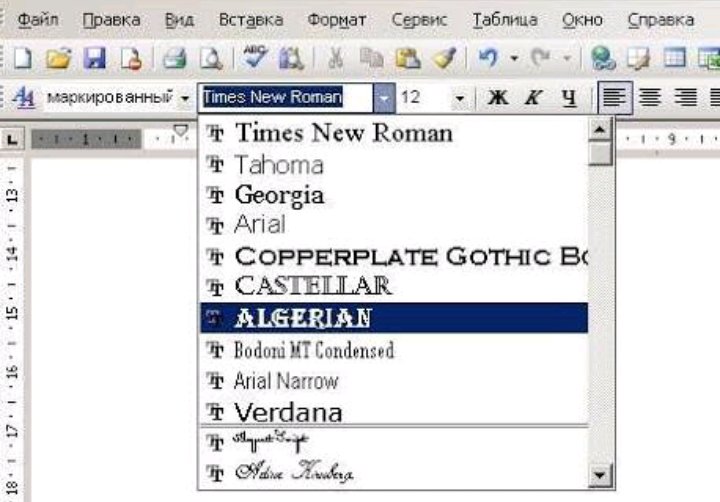
Браузер посетителя может отобразить только те шрифты, которые установлены в его операционной системе.
На этой странице приведен список русифицированных шрифтов, включённых в каждую версию Windows. Такие шрифты называют безопасными шрифтами для браузеров.
| Шрифт | — Arial |
| Шрифт | — Arial Cyr |
| Шрифт | — Arial Black |
| Шрифт | — Book antiqua |
| Шрифт | — Bookman old style |
| Шрифт | — Calibri |
| Шрифт | — Cambria |
| Шрифт | — Candara |
| Шрифт | — Century |
| Шрифт | — Century gothic |
| Шрифт | — Comic Sans Ms |
| Шрифт | — Consolas |
| Шрифт | — Constantia |
| Шрифт | — Corbel |
| Шрифт | — Courier |
| Шрифт | — Courier New |
| Шрифт | — Courier, monospace |
| Шрифт | — Cursive |
| Шрифт | — Franklin Gothic |
| Шрифт | — Gabriola |
| Шрифт | — Garamond |
| Шрифт | — Georgia |
| Шрифт | — Helvetica |
| Шрифт | — Impact |
| Шрифт | — Lucida console |
| Шрифт | — Lucida Sans Unicode |
| Шрифт | — Mistral (Mistral) |
| Шрифт | — monospace |
| Шрифт | — Monotype Corsiva |
| Шрифт | — MS Sans Serif |
| Шрифт | — MS Serif |
| Шрифт | — Palatino Linotype |
| Шрифт | — Sans-serif |
| Шрифт | — Segoe print |
| Шрифт | — Segoe script |
| Шрифт | — Sylfaen |
| Шрифт | — Tahoma |
| Шрифт | — Times New Roman |
| Шрифт | — Trebuchet ms |
| Шрифт | — Verdana |
Примеры русифицированных шрифтов
Примеры шрифтов с названиями.
Наиболее известная классификация шрифтов — по их анатомииНа первый взгляд кажется, что за всю историю письменности придумано так много шрифтов, что разобраться в них просто невозможно. На самом деле все гораздо проще и все эти бесконечные вариации окружностей и палочек легко умещаются в стройную и простую систему.
Все шрифты делятся на четыре большие группы, как времена года или стороны света:
- Антиква (с засечками)
- Гротеск (без засечек)
- Рукописные (имитирующие человеческий почерк)
- Акцидентные (для заголовков и плакатов)
Антиква
Стиль: академический, классический, традиционный, консервативный, элегантный.
Применение: деловые газеты, научные статьи, книги, учебники, документация.
Если бы шрифты можно было бы сравнить с цивилизациями, антиква, несомненно, была бы представителем западной. Эти шрифты формальны, строги и имеют самую длинную историю. У них традиции и манеры. Особенность антиквы, как уже говорилось, засечки — накрахмаленные воротнички и манжеты букв, элементы, которые делают шрифт устойчивее, основательнее, аккуратнее.
Антикве хорошо удается передавать смысл деловых документов, научных справочников и статей, больших объемных текстов. Бизнесмен с газетой скорее всего пробегает глазами антикву, студент, сдающий сессию, имеет дело с засечками.
Антиква старого стиля
Скругление засечек в местах примыкания к основному штриху и наклонная ось овальных элементов, умеренная контрастность.
Переходная антиква
Разница между основными и соединительными линиями в переходной антикве более явная, чем в старом стиле, но менее четкая, чем в антикве нового стиля.
Антиква нового стиля
Отличается более сильным контрастом между основными и соединительными линиями, строго вертикальными овалами, тонкими и длинными засечками.
Брусковая антиква
Разница между основными и соединительными линиями либо малозаметна, либо ее нет совсем, засечки мощные, прямоугольной формы. Как, например:
Гротеск
Стиль: современный, легкий, нейтральный, функциональный.
Применение: деловые, технические и электронные документы, учебная литература, архитектура, интернет и цифровые технологии.
Это, несомненно, шрифтовой север — минималистичный, четкий, функциональный и прямолинейный, как шкаф из Ikea, не терпящий никаких излишеств, как например засечки антиквы или росчерки рукописных шрифтов. Эти элементы, как атавизм, исчезли за ненадобностью. Гротескные шрифты — это новая история, конструктивизм и Баухаус, космос и компьютеры. Лента Фейсбука — гротескный Gotham. Компании Microsoft, Panasonic и даже NASA.
Старые гротески
Переходное звено в шрифтовой эволюции от антиквы до гротеска, буквы с небольшим контрастом. Примеры: Franklin Gothic, Akzidenze Grotesk
Новые гротески
Самые нейтральные, одноширинные шрифты почти без контраста. Примеры: MS Sans Serif, Arial, Helvetica, Univers.
Гуманистические гротески
Имеют большую контрастность в толщине штрихов. И гуманистическими они названы не случайно, а потому что напоминают рукописные (пером).
Примеры: Gill Sans, Frutiger, Tahoma, Verdana, Optima, и Lucide Grande.
Геометрические гротески
Как ясно из названия, строятся на основе геометрических форм. Пример: Futura, Geometria.
Рукописные шрифты
Стиль: поэтический, художественный, декоративный.
Применение: оформление приглашений, альбомов, изысканные заголовки, вывески, поздравительные открытки.
Представьте себе сосредоточенного китайского мастера, выводящего пером иероглифы. Да, рукописные шрифты прекрасны, непостоянны и изящны, как восток. Они кружат своими росчерками, как турецкие дервиши, и чаще похожи на арабскую вязь и иероглифы. В рукописных шрифтах слишком много непостоянства, поэтому они кажутся человечнее и могут служить классической поэзии (как, например, формальные) и современному уличному искусству (как неформальные). Но слишком много на них не прочитаешь — в больших объемах они становятся приторными, как халва. Рукописные шрифты легко отличить по окончанию sсript в названии.
Формальные рукописные
Неформальные рукописные
Не такие старомодные как формальные и в принципе, похожи на большинство почерков современного человека, не обладающего каллиграфическим навыком. Примеры: Mistral и Brush.
Акциндентные шрифты
Стиль: декоративный, народный, фантазийный.
Это все странные, стилизованные, художественные, дизайнерские и слегка ненормальные шрифты. Читать с их помощью большие объемы текста – получится едва ли. Они лишь могут обрамлять его, быть эдакой вишенкой на торте. Акцидентные не знают правил, их начертания ограничиваются только фантазией дизайнера. Их уместно сравнить с пестрым многообразием юга: экзотической флорой и фауной джунглей или магическими орнаментами африканских племен. Реклама, вывески, заголовки, логотипы, словом все, что умещается в двух-трех словах — вот ареал обитания этой группы.
Шрифт, пожалуй, один из самых значимых, интересных, но в то же время сложных инструментов в арсенале веб-дизайнера.
1. Шрифт с засечками (Serif)
Вообще, сериф (Serif) переводится с английского как засечка, небольшой выступ, короткий штрих у основания и в верхней части буквы или символа. Большая группа шрифтов с засечками включает в себя шрифты старого стиля, современного стиля и египетского стиля.
Старый стиль
Шрифты старого стиля основаны на технике письма клинописью. Засечки строчных букв всегда располагаются под углом, а все изогнутые линии буквенных форм имеют переход от толстого штриха к тонкому. Если провести линию через тонкие части закругленного штриха, то она всегда будет диагональной.
Шрифты старого стиля считаются лучшими для набора длинного текста. Во-первых, у них крайне мало отличительных особенностей, мешающих чтению. А во-вторых, глаз как бы цепляется за засечки, что облегчает сам процесс чтения.
Современный стиль
Еще их называет Modern или Didone. Внешний вид шрифтов современного стиля отличается некой отчужденностью. Здесь уже нет явного подражания клинописи. У таких шрифтов засечки горизонтальные и более тонкие, явно выраженный, контрастный переход от толстой линии к тонкой и очевидный вертикальный нажим.
Такие шрифты очень хорошо смотрятся при написании крупным кеглем. Однако, из-за резкого перехода от толстой линии к тонкой, такие шрифты не годятся для длительного чтения. Поэтому их лучше всего использовать для написания заголовков и логотипов.
Египетский стиль
Этот стиль шрифта иногда называется Claderon, по названию первого шрифта этой группы. Их отличительная особенность — едва заметный переход или контраст от более толстой линии к тонкой, а иногда и вообще его отсутствие.
Также засечки строчных букв у таких шрифтов горизонтальные и толстые. Еще одно название этой группы Slab Serif. В переводе с латинского slabs значит прямоугольные.
Поскольку штрихи у шрифтов египетского стиля более плотные и единообразные, то такой шрифт идеально подходит для длинных текстов. Но при этом следует учесть, что вся страница в целом будет выглядеть более темной. Этот стиль получил широкое распространение при наборе детских книжек.
2. Рубленый шрифт
Слово sans в переводе с французского означает «без». Таким образом название этой группы переводится как «без засечек». В таких шрифтах практически нет нажима при переходе от более толстой линии к тонкой. Из-за этого они выглядят более единообразно по толщине.
Считается, что шрифты с засечками более удобны для чтения. Однако, что касается веб-дизайна, то тут нет однозначного мнения. Это связано с техническими особенностями монитора. Я для себя выбрала шрифт с засечками, но на многих сайтах я вижу, что используются рубленые шрифты для основного текста, тот же Arial или Tahoma.
Так что тут уж на ваше усмотрение. Скачать некоторые вы можете на моем сайте.
3. Рукописный шрифт
Техника создания таких шрифтов включает в себя написание вручную специальной кисточкой или ручкой для каллиграфии. Рукописные шрифты не подходят для написания длинных текстов, особенно из одних прописных букв. Но они очень красиво смотрятся, набранные крупным кеглем. Так что, как декоративный элемент оформления они просто незаменимы. Скачать вы можете в соответствующей подборке.
4. Декоративный шрифт
К этой категории относятся большинство шрифтов, не попадающих в остальные категории. Декоративных шрифтов очень много и их количество увеличивается день ото дня. Из-за своей яркой экстравагантности такие шрифты стоит применять дозировано и аккуратно. Это могут быть логотипы, заголовки, надписи. Примеры представлены у меня на сайте.
До сих пор не обрела полной отчётливости, даже при их разделении на различные классы и категории, описанные в разное время преданными поклонниками искусства типографики.
Одни могут подходить к классификации шрифтов индивидуально, другие — рассматривать её в виде общей структуры, я же искренне верю, что это различие подходов сохранится навсегда. Дело не в проведении классификации как таковой, главным объектом нашего интереса должна быть специфика работы дизайнеров над каждым отдельным неповторимым вариантом начертания.
Структура символа
Давайте начнём с рассмотрения структуры символа:
1. Строка основания — воображаемая линия, несущая на себе все символы, их «насест».
2. Линия прописных — воображаемая линия, проведённая по макушкам заглавных букв. Она может равняться высоте верхних выносных элементов строчных букв, но может и отличаться от неё, в зависимости от начертания.
3. Линия строчных — горизонтальная линия, прочерченная по макушкам большинства строчных букв, таких как “a”,”c”, “e”, “x”.
4. Подстрочный (нижний выносной) элемент — часть букв “g”, “j”, “p”, “q”, “y”, расположенная ниже строки основания.
5. Надстрочный (верхний выносной) элемент — противоположность подстрочного. Венчает строчные буквы “b”, “d”, “f”, “h”, “k”, “l”, “t”.
Все мы можем обсуждать классификации шрифтов с засечками или без. К сожалению, не слишком многие понимают подлинное различие между ними:
6. Засечка — дополнительный штрих в изображении буквы. Шрифт без засечек, как можно догадаться, их лишён; края его символов не имеют «ограничителей».
7. “x”-высота — высота строчной буквы “x”. На первый взгляд, это значение может показаться, как бы, лишним, однако, в CSS-программировании оно принято за единицу измерения (главным образом, потому, что у строчной буквы “x” нет ни верхних, ни нижних выносных элементов).
01. Шрифты «старого стиля» или «Альдине»
Эти шрифты были разработаны печатниками эпохи Возрождения, и содержат множество элементов, заимствованных из древнеримского письма. Ряд специалистов считают «старый стиль» синонимом «Альдине», другие причисляют «Альдине» к разновидностям «старого стиля» (вместе с гуманистическими шрифтами).
Их отличительные характеристики: слабый/средний контраст между широкими и узкими штрихами, а также округлые, как правило, засечки. Отчётливость этих шрифтов в текстах для чтения великолепная.
Наиболее популярные шрифты этой группы: Garamond, Minion Pro, Palatino, Centaur и Bembo.
02. Шрифты промежуточного типа
Как следует из её названия, эта группа совмещает в себе элементы «старого стиля» и современных шрифтов. Шрифты этого типа характеризуются следующими отличиями: высота прописных букв равна высоте строчных с верхними выносными элементами, стыки штрихов покатые или плоские, осевые компоненты тоже слегка смещены или уплощены. Округлые засечки отчётливы более, чем у шрифтов «старого стиля», но менее, чем у современных.
Самый широкоиспользуемый шрифт данного семейства — однозначно, Times New Roman.
03. Современные или дидотовские шрифты
У этих шрифтов очень заметные особенности: тонкие горизонтальные и массивные вертикальные штрихи, резко контрастирующие между собой, а также лишённые округлости вертикально направленные засечки.
Современные шрифты появились в восемнадцатом столетии, их разработчиками были семья французских печатников Дидо (Didot) и итальянский издатель Джамбаттиста Бодони (Giambattista Bodoni).
Наиболее значимые представители этой группы шрифтов: Century, Bodoni, Didot и Bookman.
04. Шрифты с прямыми засечками
Современные, «нового стиля» шрифты получили широкую известность, однако, шрифты данной группы имеют собственные яркие особенности. Прямоугольные и более крупные засечки; однородный по плотности элементов контур с обычно перпендикулярными ровным краям штрихов засечками. Пять отдельных подгрупп шрифтов: «египетские», «Кларендон», «итальянские», «латинские» и «этрусские».
Примеры шрифтов с прямыми засечками: Rockwell, Memphis, Figaro и Excelsior.
05. Шрифты без засечек
Этот вариант начертания был разработан в начале девятнадцатого века, но добиваться популярности ему пришлось ещё почти сто лет. Основная его особенность — полное отсутствие засечек.
Эти шрифты впечатляют своей простотой и практичностью. Их считают наиболее обобщённой формой графического представления алфавита.
Самые значимые представители этой группы: Helvetica, Arial, Futura, Century Gothic и Gill Sans.
06. Готические рукописные шрифты
Они словно вышли из-под пера усердного каллиграфа где-нибудь в Европе времён Гутенберга, что помогает очень легко установить их происхождение. Готические рукописные шрифты отличаются изысканной витиеватостью букв и применяются, в основном, при оформлении дипломов, приглашений и прочих официальных бумаг/документов. Лучше всего использовать только их строчные символы, без заглавных букв. Другие названия шрифтов данной группы — Старинное английское письмо (Black Letter) или Староанглийская готика (Old English).
Наиболее известные среди этих шрифтов: Cloister Black Lite, Black Forest и Linotext.
07. Рукописные шрифты
Своим начертанием они имитируют письмо от руки. Смотрятся естественно, а их сильно закруглённые символы напоминают связную скоропись.
Шрифты данной группы не отличаются хорошей разборчивостью.
Удачные образцы таких шрифтов: Rage Italic и Cristopherhand.
08. Декоративные или «галантерейные» шрифты
Декоративные шрифты легче сгруппировать. Их нельзя отнести ни к одной из вышеперечисленных категорий. Они предназначены, главным образом, для того, чтобы придавать надписям определённое настроение, помогать им выделяться своей оригинальностью, и именно поэтому применение таких шрифтов в печати и веб-среде весьма ограничено.
09. Значки или шрифты-комплекты типографских пометок
Кто-то здорово придумал взять и заменить буквенно-цифровой набор символов значками, рисунками, картинками, — так и появились орнаментальные символьные комплекты. Область их применения трудно чётко определить, но иногда они могут очень пригодиться, а бывают и весьма выразительными внешне.
Не могу сказать, что предложенная в моей статье классификация шрифтов — единственно верная, но в её основу легли мои лучшие наработки за долгие годы практики; это всего лишь удачная возможность сравнить свойства различных шрифтов, а также, что важнее, выделить для себя те структурные элементы, наличие которых позволяет включить отдельную буковку в обширное семейство (шрифтов).
Если ваша классификация лучше моей, я бы с удовольствием познакомился с ней через раздел комментариев.
Ознакомление с начертаниями шрифтов начнем с самых простейших видов. К простейшим шрифтам относятся шрифты рубленые и плакатные (гротеск).
Изучающему начертание различных шрифтов для простоты понимания формы и конструкции букв и цифр предлагается пользоваться модульной сеткой. Модульная сетка представляет собой сетку, состоящую из квадратов, т.е. как бы канву, по которой можно выполнять построение букв и цифр шрифта. За толщину основного штриха берется модуль (единица измерения), равный ширине 1 клетки. Таким образом, по модульной сетке можно брать различные пропорции букв шрифта.
Буквы каждого шрифта подразделяются на три группы: узкие, нормальные и широкие. К узким буквам относятся Б, В, Г, Е, Р, Ь, Ъ; к нормальным — А, Д, 3, И, К, Л, Н, П, Т, У, Ч, Ц, Ч, Я; а к широким — Ж, М, О, С, Ф, Ш, Ы, Э, Ю (рис. 4.16).
Таким образом, сами по себе буквы, имея разные пропорции, создают впечатление разнообразия.
Кроме того, буквы подразделяются на прямоугольные и округлые.
В зависимости от техники начертания шрифты бывают рукописные, их выполняют от руки с помощью плакатных перьев, кисти; рисованные, их выполняют карандашом (а затем буквы заполняются краской). К рисованным шрифтам относятся также шрифты, выполняемые с помощью трафаретов; рельефно-объемный или гравированный (который выполняют на различных материалах — камне, дереве, металле с помощью специальных инструментов — резцов и др.).
По технике начертания наиболее простым видом шрифта является плакатный шрифт «гротеск», все буквы и цифры которого имеют одинаковую толщину штрихов. Он не имеет засечек. Многообразие плакатных шрифтов позволяет художнику делать соответствующий выбор пропорций букв, т.е. брать не только уже имеющиеся шрифты, но как бы создавать собственные.
На рис. показаны образцы двух разновидностей плакатного шрифта. Горизонтальные штрихи у букв проходят точно по середине их высоты.
А на этом рис. они подняты немного вверх.
Модульная сетка в данном примере имеет уже неодинаковые размеры, в результате чего буквы более устойчивы, стройны и красивы.
Плакатный шрифт, показанный на рис. 4.16, имеет три разновидности пропорции букв, что придает ему большую динамичность, хотя горизонтальные штрихи проходят у букв точно по середине. Модульная сетка, начерченная для каждой буквы, точно определяет их размеры. Нетрудно заметить, что буквы, имеющие округления, как например — Б, В, Р, Ь, в местах округлений немного шире стороны прямоугольника, положенного в основу пропорции этих букв. На второй строчке буквы чуть шире предыдущих, но не все они вписываются в прямоугольник целиком. Буква А, например, в своей нижней части выходит за стороны прямоугольника, буква 3, наоборот, немного уже. Целиком вписываются в прямоугольник лишь буквы И, К, Л, Н, П, У. Остальные — Т, Ч чуть меньше.
Все эти изменения букв сделаны с учетом зрительного восприятия, вызванного психофизиологией нашего зрения. Например, вертикальные линии (штрихи) в буквах нам кажутся тоньше горизонтальных, поскольку средняя геометрическая ось не совпадает с оптической.
Установлено, что для округлых букв их округлость должна выходить за рамку прямоугольника примерно на Уго- Узо высоты буквы (обычно этот размер берется приблизительно). При начертании слов важно учитывать межбуквенный просвет. При сочетании некоторых букв межбуквенный просвет делать не надо.
Начертание букв плакатным пером осуществляют двумя способами. В первом случае обводят сначала все вертикальные прямые. Обводку вертикальных штрихов выполняют движением пера сверху вниз, держать его нужно с небольшим наклоном в сторону движения. После высыхания туши движением пера слева направо обводят горизонтальные штрихи, причем сначала все верхние штрихи, затем средние, нижние, а в последнюю очередь и наклонные.
Во втором случае обводку букв производят снизу. Наибольшая трудность здесь состоит в закруглениях букв и цифр. При выполнении закруглений перо надо вести почти вертикально. Для этого необходимо сначала потренироваться на отдельном листе.
В наиболее ответственных надписях для придания шрифту большей строгости и аккуратности буквы обводят плакатным пером с помощью линейки.
Одну линейку кладут вниз, а другую сверху нее. Верхнюю линейку сдвигают немного вперед и по ней чертят буквы. В таком случае тушь не подтекает под линейку. Не рекомендуется пользоваться при этом тонкими металлическими или тонкими пластмассовыми линейками.
Приведенные выше плакатные шрифты носят название плоских силуэтных. Кроме них имеются и объемные шрифты, представляющие собой разновидность плакатных шрифтов.
При составлении композиции текста художники применяют декоративные шрифты, украшенные рисункам или орнаментом, что придает им своеобразную форму.
Кроме прямых шрифтов в декоративно-оформительском искусстве применяют курсивные (наклонные) шрифты. Наклонив буквенные знаки шрифта под углом 75°, можно получить варианты курсивных шрифтов (рис. ниже). Буквы курсивных шрифтов пишут как отдельно друг от друга, так и вместе. Иногда соединения букв в курсивном шрифте ухудшают его удобочитаемость.
При одинаковой толщине обводки штрихов по методике Г. В. Гречихо курсивный шрифт пишут стеклянными трубочками, фломастерами и чертежными перьями «редис» (рис.
ниже). Курсивные шрифты выполняют чаще всего прямыми плакатными перьями, а также плоско отточенными палочками. Вариантов курсивных шрифтов много, и возможности для составления собственных разновидностей курсивных шрифтов неограниченны.
Красота шрифта заложена в самой конструкции буквы, в умении найти гармоническое сочетание размеров ее частей. На рис. ниже показан образец рукописного жирного курсивного шрифта, автором которого является известных советский художник В. К.Тоотс.
Рукописный курсивный шрифт наиболее доступен и быстр в написании и самый скорый. Его обычно пишут ширококонечным пером («рондо»), сохраняя при этом постоянное положение руки и глаз по отношению к листу бумаги. Штрих выполняют сразу, без изменения угла наклона. Штрихи пишут сверху вниз и слева направо. Для написания текстов ширококонечным пером лучше всего использовать гладкую белую бумагу.
Рассмотрим следующую группу шрифтов, относящуюся к контрастным. Эта группа носит общее название «антиква».
К разновидностям антиквы относят академический шрифт, который имеет несколько вариантов, а также архитектурный. Буквы и цифры этих шрифтов в большинстве своем имеют вверху и внизу засечки. Рисунок засечек представляет собой некоторую сложность при начертании букв.
Познакомимся с формой и конструкциями букв и цифр академического шрифта (рис).
В учебных целях шрифт выполнен с помощью модульной сетки, которая позволяет наглядно увидеть особенности начертания каждой буквы, цифры и сравнить их между собой. Ширина букв неодинакова и берется в зависимости от формы буквы. Например, наименьшую ширину — 4,5 модуля имеет буква 3. Буквы Б, В, Г, Е, И, Н, П, Р, Ч имеют ширину 5 модулей, т.е. пропорция составляет отношение 5:8, буквы Э, Ц — 5,5 модуля, буквы А, Л, Т, У, Ц, Ъ, О, Я — 6 моду-лей (6: 8). К более широким буквам относятся Ж, Ф, Ш, Ы, Д — 7 модулей. Самые широкие — Ю, Щ — 7,5 модулей.
В некоторых случаях художник меняет по необходимости пропорции букв шрифта. Тогда строят прямоугольник с нужным со-отношением сторон.
Внутри прямоугольника наносят модульную сетку. Число ее делений по ширине и высоте должно соответствовать принятому числу модулей для взятой буквы данной разновидности шрифта.
Если вы уже познакомились с основами типографии и знаете, где можно найти подходящие для вас шрифты, то самое время познакомиться с классификацией шрифтов и их типами. В наше время существует достаточно большое количество самых разнообразных шрифтов. Они бывают как платные, так и бесплатные.
Основные группы шрифтов
Сейчас существует очень много различных шрифтов. Все они имеют специфические характеристики, благодаря которым их можно разделить на группы:
Serif (с засечками)
Такие шрифты обычно применяют в печати. Причиной этого является удобство их чтения, которое и делает их очень популярными. Этот тип шрифтов привлекателен небольшими линиями на концах букв. Свое применение он получил в книгах, разных журналах и газетах. В свою очередь, шрифты с засечками помогут вашему сайту приобрести некую элегантность и сделать внешний вид веб-дизайна более утонченным.
Slab serif (прямоугольные засечки)
Использование такого типа шрифтов придаст вашему сайту уникальности и сделает его внешний вид довольно стильным. Прямоугольные засечки тяжело читаются и поэтому их не рекомендуют использовать в тексте, которым вы наполняете тело сайта. Лучшего всего их использовать при оформлении заголовков, что придаст им более интересный вид и визуально отделит их от основной части текста.
Script (пропись)
Лучше всего эти шрифты используются для дополнения декоративных элементов вашего дизайна. Применяя шрифты прописью, будьте особо осторожны, эксплуатируя их в своих заголовках, а также в тексте тела сайта, потому как их чтение является довольно затруднительным процессом для посетителей.
Blackletter (готический шрифт)
Этот шрифт имеет декоративный вид. Если вы хотите разбавить ваш веб-дизайн чем-нибудь старинным, то вам следует воспользоваться именно этим шрифтом. Зачастую эти шрифты используют различные рестораны на своих вывесках.![]()
Sans serif (без засечек)
Буквы не будут иметь засечек. Они довольно схожи со шрифтами, которые имеют засечки и будут замечательно смотреться в тексте любого интернет ресурса или в заголовках. Обычно их применяют на компьютере, потому как читать их намного удобней, когда шрифт имеет мелкие размеры. Эти шрифты могут помочь сделать ваш проект более простым, а его дизайн — более минималистичным. На сегодняшний день San serif — это самый популярный шрифт, который дизайнеры используют для текста статей, размещаемых на своих веб-сайтах.
Handwriting (рукописный шрифт)
С применением шрифта такого типа ваш текст будет выглядеть так, будто его кто-то написал своей рукой. Он может послужить для веб-проекта неплохим декоративным дополнением, что в свою очередь сделает его уникальным и неповторимым. Лучше всего использовать шрифт только для выделения информации, на которую вы хотите обратить внимание читателя.
Decorative (декоративный)
Эти шрифты включают в себя все существующие типы забавного характера и являются довольно оригинальными.
Небольшой их минус заключается в том, что их очень трудно прочитать. Если вы хотите, чтобы ваш веб-проект имел необыкновенное оформление текста, то можете смело их использовать.
Подборка и совмещение шрифтов
Разнообразие шрифтов огромно, а значит комбинаций их совмещения еще больше. Поэтому правильная подборка шрифтов занимает очень много времени. Это довольно непростой процесс, при котором вы всегда должны основываться на стиле вашего интернет проекта и на предпочтениях ваших посетителей.
Во-первых, в начале этого процесса вы должны определиться с выбором шрифта, который будете использовать в тексте тела сайта, он же станет основным для всего вашего проекта. Зачастую для тела сайта выбирают шрифт с засечками или же без них. Это даст вам уверенность в том, что ваш сайт будет читабельным, и поэтому поиск шрифтов следует проводить непосредственно именно в этих двух группах.
Обратите свое внимание и на то, чтобы шрифт, выбранный вами, имел разнообразные стили.
Это позволит вам быть более гибкими при использовании их в веб-проекте. Хорошим способом понять, подходит ли вам тот или иной шрифт, будет его тестирование на больших блоках, например в заголовках, параграфах и т.д.
Во-вторых, вам обязательно нужно определить еще один шрифт, который вы будете использовать в некоторых заголовках. Определенных правил такого выбора не существует, но опытные дизайнеры рекомендует подбирать такой шрифт, который будет отличаться от основного, используемого вами для тела сайта. Таким образом, вы сможете сделать заголовки на вашем сайте более привлекательными для пользователей. Лучше использовать шрифт для тела сайта слегка измененный, например, сделав его полужирным.
Неплохим вариантом оформления текста является смешивание и соединение группы шрифтов заголовков с засечками с основным текстом сайта, который будет без засечек. Провидите этот эксперимент, и вы увидите, что эти две группы очень гармонично сочетаются друг с другом, создавая красивый дизайн типографии.
В-третьих, если вы хотите обратить внимание ваших пользователей на какие-то определенные элементы текста и сделать их более видимыми, то вам следует внести еще один шрифт в дизайн. В этом случае поэкспериментируйте с рукописным и декоративным шрифтом, так как именно они позволяют привлечь внимание посетителей веб-сайта.
Как смешивать и использовать шрифты в тексте
Рассмотрим несколько принципов совмещения шрифтов, которые позволят добиться красивого оформления текста.
Сайт должен быть читабельным
Подбирая шрифт для текста тела сайта или заголовка, обязательно следует помнить то, что он должен быть легко читаем пользователем. Конечно, читаемость некоторых шрифтов напрямую зависит от правильных их настроек: необходимо следить за тем, чтобы был выбран соответствующий размер шрифта, высота строк, цвета. Перед применением в веб-дизайне каких-либо шрифтов проверьте, как они будут смотреться в разных цветах. Таким образом, вы сможете понять, подходит ли вам тот или иной цвет.
Это правило имеет пару исключений, о которых следует помнить всегда. К примеру, вы разрабатываете веб-дизайн для детского интернет-проекта и, возможно, вам захочется применить один из видов декоративного шрифта, который понравится детям. В этом случае старайтесь придерживаться шрифта с засечками и без засечек. Соблюдать это правило необходимо, потому как проведенные исследования доказали, что эти шрифты намного легче читаются, поэтому выбор декоративных шрифтов будет не самым лучшим вариантом в данном случае.
Не используете большое количество разных шрифтов
Создавая дизайн проекта, старайтесь не использовать большое количество шрифтов. Оптимальным количеством для использования будет три шрифта. Этому есть несколько причин:
При использовании сервисов шрифтов каждый шрифт, добавленный вами, будет способствовать увеличению скорости загрузки страницы сайта.
Присутствие большего количества шрифтов на страницах сайта отвлекает посетителей, из-за чего им будет тяжелей сконцентрировать свое внимание на чтении контента.
Применяя не более трех шрифтов, вы экономите свое время, но при этом веб-сайт выглядит отлично.
Не используйте неподходящие сочетания
Комбинирование нескольких шрифтов при написании заголовков сайта или соединение большого количества различных шрифтов – это очень плохая задумка. Такие комбинации являются рискованными и могут принести вам много проблем.
Просматривая шрифты на веб-сервисе Typekit, вы имеете возможность устанавливать необходимые для вас фильтры, которые помогут разобраться в том, какие шрифты лучше применять для заголовков или параграфов, что будет очень полезным инструментом во время разработки дизайна.
Примеры объединения шрифтов
Для примера рассмотрим страницы нескольких сайтов, где грамотно подобраны шрифты.
Заголовки:
Sentinel (serif slab)
Параграфы:
Gotham Narrow (sans-serif)
На этих примерах мы можем наблюдать, что заголовки и подзаголовки имеют шрифт с прямоугольными засечками.
Он выступает в качестве контраста к основному тексту сайта и является простым и легко читаемым шрифтом. Этот дизайн имеет единообразность. От него можно добиться многого, лишь изменив цвет и его стиль.
Заголовки и параграфы:
Freight Text Pro (serif)
Остальное:
Freight Sans Pro (san-serif)
На этом примере мы можем наблюдать, как используют только один шрифт для заголовков и параграфов. Это выглядит довольно здорово, потому как заголовки имеют более жирный и крупный вид.
Так же здесь мы можем наблюдать и один шрифт без засечек, который автор использует на кнопках сайта и информации о сообщениях.
Заголовки:
PMN Caecilia (slab serif).
Параграфы:
Gill Sans (sans-serif)
Дизайнеры этого сайта создали очень утонченный и красивый дизайн своего веб-ресурса. Здесь отсутствуют какие-либо раздражители и жирные шрифты. Они остановили свой выбор на тонком шрифте для заголовков и простом шрифте для текста тела сайта.
Присутствующие на этом ресурсе оба семейства шрифтов имеют отличное сочетание, что позволяет посетителю с легкостью читать весь текст.
Заголовки и параграфы:
Skolar (serif)
Дизайнеры этого сайта используют только один шрифт с засечками. Но, несмотря на такое неординарное решение специалистов, заголовки и параграфы между собой имеют видимую разницу. Все это благодаря тому, что здесь используются специфические стили, цвета и размеры шрифта.
Шрифты, общие для всех (актуальных) версий Windows, и их Mac-эквиваленты / Хабр
Введение
В данном списке перечислены шрифты, общие для всех актуальных на данный момент операционных систем Windows (фактически начиная с Windows 98), и их эквиваленты в Mac OS. Такие шрифты иногда называют «безопасными шрифтами для браузеров» (
browser safe fonts). Это небольшой справочник, которым я пользуюсь, когда делаю Web-страницы и думаю, что он будет полезен и Вам.
Если Вы новичок в web-дизайне, то может быть думаете что-нибудь типа: «Почему это я должен ограничиваться таким небольшим набором шрифтов? У меня есть огромная коллекция прекрасных шрифтов!» Дело в том, что браузер посетителя может отобразить только те шрифты, которые установлены
в егооперационной системе (
прим.
переводчика:в настоящее время уже есть возможность применять фактически любые шрифты при оформлении страниц
используя CSS 3и его новое свойство
@font-face; правда, поддерживают эту функцию пока ещё далеко не все браузеры), а это означает, что
каждыйпосетитель Вашей страницы должен быть обладателем выбранных Вами шрифтов. Поэтому Вы должны использовать только те шрифты, которые есть в каждой операционной системе. К счастью, в
CSSесть свойство
@font-family, облегчающее эту задачу.
Также Вам может быть интересен список шрифтов, включённых в каждую версию Windows.
Список
| Значение @font-family | Windows | Mac | Семейство |
|---|---|---|---|
| Arial, Helvetica, sans-serif | Arial | Arial, Helvetica | sans-serif |
| «Arial Black», Gadget, sans-serif | Arial Black | Arial Black, Gadget | sans-serif |
| «Comic Sans MS», cursive | Comic Sans MS | Comic Sans MS5 | cursive |
| «Courier New», Courier, monospace | Courier New | Courier New, Courier6 | monospace |
| Georgia, serif | Georgia1 | Georgia | serif |
| Impact,Charcoal, sans-serif | Impact | Impact5, Charcoal6 | sans-serif |
| «Lucida Console», Monaco, monospace | Lucida Console | Monaco5 | monospace |
| «Lucida Sans Unicode», «Lucida Grande», sans-serif | Lucida Sans Unicode | Lucida Grande | sans-serif |
| «Palatino Linotype», «Book Antiqua», Palatino, serif | Palatino Linotype, Book Antiqua3 | Palatino6 | serif |
| Tahoma, Geneva, sans-serif | Tahoma | Geneva | sans-serif |
| «Times New Roman», Times, serif | Times New Roman | Times | serif |
| «Trebuchet MS», Helvetica, sans-serif | Trebuchet MS1 | Helvetica | sans-serif |
| Verdana, Geneva, sans-serif | Verdana | Verdana, Geneva | sans-serif |
| Symbol | Symbol2 | — |
| Webdings | Webdings2 | — |
| Wingdings, «Zapf Dingbats» | Wingdings2 | Zapf Dingbats2 | — |
| «MS Sans Serif», Geneva, sans-serif | MS Sans Serif4 | Geneva | sans-serif |
| «MS Serif», «New York», serif | MS Serif4 | New York6 | serif |
1 Шрифты Georgia и Trebuchet MS поставляются вместе с Windows 2000/XP и включены в пакет шрифтов IE (да и вообще поставляются со многими приложениями от Microsoft), поэтому они установлены на многих компьютерах с ОС Windows 98.
2 Символьные шрифты отображаются только в Internet Explorer, в остальных браузерах они обычно заменяются на стандартный шрифт (хотя, например, шрифт Symbol отображается в Opera, а Webdings — в Safari).
3 Шрифт Book Antiqua практически идентичен Palatino Linotype; Palatino Linotype поставляется с Windows 2000/XP, а Book Antiqua — с Windows 98.
4 Обратите внимание, что эти шрифты не TrueType, а bitmap, поэтому они могут плохо выглядеть с некоторыми размерами (они предназначены для отображения в размерах 8, 10, 12, 14, 18 и 24 pt при 96 DPI).
5 Эти шрифты работают в Safari только в стандартном начертании, но не работают при выделении жирным или курсивом. Comic Sans MS также работает жирным, но не курсивом. Другие Mac-браузеры, кажется, нормально эмулируют отсутствующие у шрифтов свойства самостоятельно (спасибо Christian Fecteau за подсказку).
6 Эти шрифты установливаются в Mac только при Classic-инсталляции
Скриншоты
- Mac OS X 10.
4.8, Firefox 2.0, ClearType включён (за скриншот спасибо Juris Vecvanags) - Mac OS X 10.4.4, Firefox 1.5, ClearType включён (за скриншот спасибо Eric Zavesky)
- Mac OS X 10.4.11, Safari 3.0.4, ClearType включён (за скриншот спасибо Nolan Gladius)
- Mac OS X 10.4.4, Safari 2.0.3, ClearType включён (за скриншот спасибо Eric Zavesky)
- Windows Vista, Internet Explorer 7, ClearType включён (за скриншот спасибо Michiel Bijl)
- Windows Vista, Firefox 2.0, ClearType включён (за скриншот спасибо Michiel Bijl)
- Windows XP, Internet Explorer 6, ClearType включён
- Windows XP, Firefox 1.0.7, ClearType включён
- Windows XP, Internet Explorer 6, Сглаживание шрифтов включено
- Windows XP, Firefox 1.0.7, Сглаживание шрифтов включено
- Windows 2000, Internet Explorer 6, Сглаживание шрифтов включено
- Windows 2000, Firefox 1.0.7, Сглаживание шрифтов включено
- Linux (Ubuntu 7.
04 + Gnome), Firefox 2.0 (за скриншот спасибо Juris Vecvanags)
Несколько примеров из скриншотов (по одному на каждую операционную систему)
Mac OS X 10.4.8, Firefox 2.0, ClearType включён
Windows Vista, Internet Explorer 7, ClearType включён
Windows XP, Internet Explorer 6, ClearType включён
Windows 2000, Internet Explorer 6, Сглажмвание шрифтов включёно
Linux (Ubuntu 7.04 + Gnome), Firefox 2.0
Прим. переводчика: статью пришлось немного переделать, т.к. Хабр не разрешает добавлять собственные стили к тексту 🙁
Шрифты
ШрифтыОбратите внимание, что
- данный документ является переводом документа «Fonts» и на данный момент находится на стадии перевода;
- данный документ может содержать неточности, опечатки и ошибки перевода;
- официальным документом по данной тематике является оригинальный документ на английском языке, расположенный на сайте W3C.
Установка свойств шрифта будет одним из самых распространённых и используемых свойств таблиц стилей. К сожалению, не существует чётко определенной и общепринятой классификации шрифтов, так как условия, относящиеся к одному семейству шрифтов, могут не подходить другим. Например, ‘italic’ обычно используется для обозначения наклонного текста, но наклонный текст также может быть обозначен как Oblique, Slanted, Incline, Cursive или Kursiv. Поэтому отображение выбора обычного свойства шрифта для конкретного шрифта является не простой задачей.
Так как не существует общепринятой, универсальной классификации
свойств шрифта, то согласование свойств вариантов шрифта должно
производится с осторожностью. Свойства сопоставляются в строго
определённом порядке, чтобы гарантировать, что результаты этого
процесса сопоставления являются как можно более последовательными
для всех агентов пользователей (при условии, что они имеют одну и
ту же библиотеку шрифтов).
- Агент пользователя создаёт (или использует) базу данных соответствующую всем CSS 2.1 свойствам шрифтов, о которых он знает. Если присутствует два шрифта с одинаковыми свойствами, то агент пользователя выбирает один из них.
- В определённом элементе и для каждого символа в этом элементе, агент пользователя собирает свойства шрифта, применяемые к данному элементу. На основании полного набора свойств, агент пользователя использует свойство ‘font-family’ для выбора предполагаемого семейства шрифта. Остальные свойства проверяются независимо от семейства в соответствии с критериями, описанными для каждого свойства. Если по всем остальным свойствам имеются совпадения, то соответствующий тип варианта шрифта соответствует данному элементу или символу.
- Если нет подходящего варианта шрифта в рамках гарнитуры ‘font-family’
подбираемого в шаге №2, и если в наборе шрифтов существует подходящая
альтернатива значению ‘font-family’, то происходит повторение шага №2,
но уже с соответствующей альтернативой ‘font-family’.
- Если присутствует соответствующий вариант шрифта, но он не содержит глиф для текущего символа и если в наборе шрифтов существует подходящая альтернатива ‘font-family’, то происходит повторение шага №2, с соответствующей альтернативой ‘font-family’.
- Если такого шрифта нет, то выбирается следующее указанное семейство,
а затем используется значение ‘font-family’ установленное агентом
пользователя по умолчанию и повторяется шаг №2, при этом используется
шрифт более соответствующий ожиданиям, который может быть установлен в
качестве шрифта по умолчанию. Если конкретный символ не может быть
отображён с помощью данного шрифта, то агент пользователя может
использовать другие способы чтобы определить подходящий шрифт для этого
символа. Агент пользователя должен отобразить каждый символ, для
которого он не имеет подходящего шрифта, а для видимого символа
выбранного агентом пользователя предпочтительней глиф
отсутствующего символа
для одного из вариантов шрифта, доступных агенту пользователя.
(Представленный выше алгоритм может быть оптимизирован для того, чтобы избежать необходимость повторять свойства CSS 2.1 отдельно для каждого символа.)
Для каждого свойства, правила согласуются с (2) представленным выше алгоритмом, следующим образом:
- ‘font-style’, первым. ‘Italic’ будет применён, если есть какой-либо вариант в базе данных шрифтов агента пользователя, помеченного ключевым словом ‘italic’ (предпочтительно) или ‘oblique’. В противном случае значения свойств должны быть точными или font-style не будет применён.
- ‘font-variant’
проверяется следующим. ‘Small-caps’ соответствует
(1) шрифту, помеченному как ‘small-caps’, (2) шрифту в котором синтезируются
заглавные символы или (3) шрифту в котором все строчные буквы заменяются
прописными буквами. Капитель шрифт может быть синтезирован с помощью
электронного масштабирования прописных букв нормального шрифта. Значению
‘normal’ соответствует нормальный (не капитель) вариант. При этом шрифт не
может не иметь нормальный вариант отображения.
Шрифт, который доступен только
в виде капители, всё равно должен иметь значение ‘normal’ и ‘small-caps’. - Следующим проверяется ‘font-weight’, он никогда не подведёт. (Смотрим ниже ‘font-weight’.)
- ‘font-size’ должен соответствовать пределу допустимых значений агента пользователя. (Как правило, размеры масштабируемых шрифтов округляются до ближайшего целого значения выражаемого в пикселях, в то время как погрешность для растровых шрифтов может составлять около 20%.) Дальнейшие вычисления, например, с ’em’ значениями в других свойствах, основываются на вычисляемом значении свойства ‘font-size’.
Значением свойства является приоритетный список имён семейств шрифтов и/или общих семейств шрифтов. В отличие от большинства других свойств CSS, значения разделяются запятой, чтобы показать, что они являются альтернативами:
body { font-family: Gill, Helvetica, sans-serif }
Несмотря на то, что многие шрифты содержат глиф
отсутствующего символа,
не стоит рассчитывать на его использование вместо символов, которых
нет в шрифте.
(Однако следует считать, что
U+FFFD
соответствует отсутствующему символу симолов кодировки).
Существует два типа указания семейства шрифтов:
- <название-семейства>
- Выбранное имя семейства шрифтов. В последнем примере, «Gill» и «Helvetica» являются семействами шрифтов.
- <общее-семейство>
- В приведённом выше примере, последнее значение указывает на общее
семейство шрифтов. Определены следующие общие семейства шрифтов:
- ‘serif’ (например, Times)
- ‘sans-serif’ (например, Helvetica)
- ‘cursive’ (например, Zapf-Chancery)
- ‘fantasy’ (например, Western)
- ‘monospace’ (например, Courier)
Дизайнерам таблиц стилей, рекомендуется указывать название общего семейства шрифтов в качестве последней альтернативы. Названия общих семейств шрифтов являются ключевыми словами и по этому они НЕ должны заключаться в кавычки.
Имена семейств шрифтов либо должны быть заключены в кавычки как
строки,
либо должны быть без кавычек в виде последовательности из одного или
более
идентификаторов.
Это означает, что большинство знаков препинания и цифр в начале каждого
названия должны быть экранированы в имена семейств шрифтов без
использования кавычек.
Например, следующие объявления недопустимы:
font-family: Red/Black, sans-serif; font-family: "Lucida" Grande, sans-serif; font-family: Ahem!, sans-serif; font-family: test@foo, sans-serif; font-family: #POUND, sans-serif; font-family: Hawaii 5-0, sans-serif;
Если последовательность идентификаторов задаётся в виде имён семейств шрифтов, то значение этих имён преобразуется в строку путём присоединения всех идентификаторов в определённой последовательности с помощью одиночных пробелов.
Чтобы избежать ошибок в объявлениях, имена семейств шрифтов, содержащие пробелы, цифры или знаки препинания, кроме дефиса рекомендуется заключать в кавычки:
body { font-family: "New Century Schoolbook", serif }
<BODY>
Имена семейств шрифтов, которые имеют такое же название,
как и значение ключевого слова (‘inherit’, ‘serif’, ‘sans-serif’,
‘monospace’, ‘fantasy’, и ‘cursive’) должны быть заключены в кавычки,
чтобы избежать путаницы между ключевыми словами и такими же именами.
Ключевые слова ‘initial’ и ‘default’ зарезервированы для будущего
использования и в случае присутствия в названиях шрифтов так же должны
подчиняться этому правилу. Агенты пользователей не должны рассматривать
эти ключевые слова, как соответствующий тип ‘<название-семейства>’.
15.3.1 Общие семейства шрифтов
Общее семейство шрифтов являются резервным механизмом, средством сохранения замысла автора в виде определённых таблиц стилей в немного худшем варианте, когда ни один из указанных шрифтов не может быть выбран. Для обеспечения оптимального типографского контроля, в таблицах стилей так же должны использоваться названия шрифтов.
Все пять общих семейств шрифтов существуют
во всех CSS реализациях (при этом не обязательно, что они будут
отображаться для пяти различных фактических шрифтов). Агенты пользователей
должны обеспечить разумные варианты по умолчанию для общих семейств
шрифтов, которые выражают характеристики каждого семейства, а также
возможностей в рамках, разрешённых применяемой технологии.
Агентам пользователей предлагается возможность разрешить пользователям самим выбирать альтернативы для общих шрифтов.
15.3.1.1
serifГлифы шрифтов serif, название которого в CSS используется в качестве термина, как правило, имеют завершающие штрихи, с расклешёнными или сужающимися концами, или с фактическими засечками окончаний (в том числе с кусочками засечек). Serif шифты, как правило, имеют определённый интервал. Они часто проявляют больше различий между толстыми и тонкими штрихами, чем шрифты общего семейства ‘sans-serif’. В CSS термин ‘serif’ используется применительно к шрифтам любой письменности, хотя некоторые другие названия могут быть более знакомы для определённых видов письма, например, такие как Mincho (Японский), Sung или Song (Китайский), Totum или Kodig (Корейский). Любой шрифт, описанный таким образом, может быть использован для представления общего ‘serif’ семейства.
Примеры шрифтов, удовлетворяющих этому описанию:
| Латинские шрифты | Times New Roman, Bodoni, Garamond, Minion Web, ITC Stone Serif, MS Georgia, Bitstream Cyberbit |
| Греческие шрифты | Bitstream Cyberbit |
| Кириллические шрифты | Adobe Minion Cyrillic, Excelsior Cyrillic Upright, Monotype Albion 70, Bitstream Cyberbit, ER Bukinist |
| Еврейские шрифты | New Peninim, Raanana, Bitstream Cyberbit |
| Японские шрифты | Ryumin Light-KL, Kyokasho ICA, Futo Min A101 |
| Арабские шрифты | Bitstream Cyberbit |
| Чероки шрифты | Lo Cicero Cherokee |
15.
3.1.2 sans-serifГлифы шрифтов sans-serif, название которого в CSS используется в качестве термина, как правило, имеют завершающие штрихи, которые являются однотонными — с небольшими бликами или без них, с пересекающимися штрихами или с другими орнаментами. Sans-serif шрифты, как правило, имеют определённый интервал. Многие шрифты из данного семейства обладают небольшим количеством различий между толстыми и тонкими штрихами, по сравнению с шрифтами общего семейства ‘serif’. В CSS термин ‘sans-serif’ используется применительно к шрифтам любой письменности, хотя некоторые другие названия могут быть более знакомы для определённых видов письма, таких как Gothic (Японский), Kai (Китайский), Pathang (Корейский). Любой шрифт, описанный таким образом, может быть использован для представления общего ‘sans-serif’ семейства.
Примеры шрифтов, удовлетворяющих этому описанию:
| Латинские шрифты | MS Trebuchet, ITC Avant Garde Gothic, MS Arial, MS Verdana, Univers, Futura, ITC Stone Sans, Gill Sans, Akzidenz Grotesk, Helvetica |
| Греческие шрифты | Attika, Typiko New Era, MS Tahoma, Monotype Gill Sans 571, Helvetica Greek |
| Кириллические шрифты | Helvetica Cyrillic, ER Univers, Lucida Sans Unicode, Bastion |
| Еврейские шрифты | Arial Hebrew, MS Tahoma |
| Японские шрифты | Shin Go, Heisei Kaku Gothic W5 |
| Арабские шрифты | MS Tahoma |
15.
3.1.3 cursiveГлифы в шрифтах cursive, название которого в CSS используется в качестве термина, как правило, имеют либо соединяющие штрихи, либо другие рукописные элементы, помимо самого курсивного шрифта. При этом символы частично или полностью связаны, и в результате запись больше похожа на надпись сделанную ручкой или кистью, чем на напечатанную надпись. Шрифты для некоторых письменностей, например, таких как арабская, почти всегда выводятся скорописью. В CSS термин ‘cursive’ используется применительно к шрифтам любой письменности, хотя некоторые другие названия, такие как Chancery, Brush, Swing и Script также используются в названиях таких шрифтов.
Примеры шрифтов, удовлетворяющих этому описанию:
| Латинские шрифты | Caflisch Script, Adobe Poetica, Sanvito, Ex Ponto, Snell Roundhand, Zapf-Chancery |
| Кириллические шрифты | ER Architekt |
| Еврейские шрифты | Corsiva |
| Арабские шрифты | DecoType Naskh, Monotype Urdu 507 |
15.
3.1.4 fantasyFantasy шрифты, используемые в CSS, в первую очередь являются декоративными, несмотря на то, что по-прежнему содержат образ символов (в отличие от Pi или Picture шрифтов, которые не отражают символы). Примеры:
| Латинские шрифты | Alpha Geometrique, Critter, Cottonwood, FB Reactor, Studz |
15.3.1.5
monospaceЕдинственным критерием monospace шрифта является то, что все символы имеют одинаковую фиксированную ширину. (Это семейство может сделать вид некоторых письменностей, например, таких как арабская, очень специфическим.) Этот эффект похож на шрифт пишущей машинки и часто используется, чтобы выделить образцы компьютерного кода.
Примеры шрифтов, удовлетворяющих этому описанию:
| Латинские шрифты | Courier, MS Courier New, Prestige, Everson Mono |
| Греческие шрифты | MS Courier New, Everson Mono |
| Кириллические шрифты | ER Kurier, Everson Mono |
| Японские шрифты | Osaka Monospaced |
| Чероки шрифты | Everson Mono |
- ‘font-style’
Значение: normal | italic | oblique | inherit Значение по умолчанию: normal Применяется: ко всем элементам Наследование: присутствует Проценты: N/A Медиа: визуальные Вычисляемое значение: как указано
Свойство ‘font-style’ выбирает между нормальным (иногда обозначают
«roman»или»upright»), курсивным и наклонным вариантом семейства
шрифтов.
Значение ‘normal’ выбирает шрифт, который в базе данных агента пользователя классифицирован как ‘normal’, тогда как ‘oblique’ выбирает шрифт, который имеет обозначение ‘oblique’. Значение ‘italic’ выбирает шрифт, который имеет обозначение ‘italic’, или, если его использование не возможно, то используется обозначение ‘oblique’.
Шрифт, который в базе данных шрифтов агента пользователя(-ей) обозначен как ‘oblique’ может быть сгенерирован путём обычного наклона нормального шрифта.
Шрифты, в названии которых присутствуют слова Oblique, Slanted или Incline обычно в безе данных шрифтов агента пользователя(-ей) помечаются как ‘oblique’. Шрифты, в названии которых присутствуют слова Italic, Cursive или Kursiv обычно помечаются как ‘italic’.
h2, h3, h4 { font-style: italic }
h2 em { font-style: normal }
В приведённом выше примере, текст, выделенный в переделах ‘h2’ будет отображаться нормальным шрифтом.
- ‘font-variant’
Значение: normal | small-caps | inherit Значение по умолчанию: normal Применяется: ко всем элементам Наследование: присутствует Проценты: N/A Медиа: визуальные Вычисляемое значение: как указано
Другим типом изменений в пределах одного семейства шрифтов является
капитель.
В капитель шрифте строчные буквы выглядят как символы верхнего
регистра, но они имеют меньший размер и немного другие пропорции. С
помощью свойства ‘font-variant’ можно выбирать такой шрифт.
Значение ‘normal’ устанавливает шрифт, который не является капителью, а вот ‘small-caps’ устанавливает капитель шрифт. CSS 2.1 допустима (но не обязательна) ситуация при которой, капитель шрифт может быть создан путём замены строчных букв нормального шрифта на масштабированные символы верхнего регистра. В качестве последнего средства, прописные буквы будут использованы в качестве замены капители.
В следующем примере, символы содержащиеся в ‘h4’ будут отображены капителью с выделением небольшой части слов наклонным шрифтом, а так же выделением наклонной капителью слов расположенных в ‘h4’ элементе:
h4 { font-variant: small-caps }
em { font-style: oblique }
В семействе шрифтов могут быть и другие варианты, например, такие как
шрифты с цифрами в старинном стиле, капитель цифрами, в виде уплотненных
или разреженных букв и прочие.
Но CSS 2.1 не имеет свойств,
позволяющих выбрать их.
Примечание: поскольку это свойство работает с текстом, который будет преобразован в верхний регистр, то для достижения такого же эффекта так же можно применять свойство ‘text-transform’.
- ‘font-weight’
Значение: normal | bold | bolder | lighter | 100 | 200 | 300 | 400 | 500 | 600 | 700 | 800 | 900 | inherit Значение по умолчанию: normal Применяется: ко всем элементам Наследование: присутствует Проценты: N/A Медиа: визуальные Вычисляемое значение: смотрите текст
Свойство ‘font-weight’ позволяет выбрать жирность шрифта.
Значения
от ‘100’ до ‘900’ образуют упорядоченную последовательность, где
каждое число обозначает жирность, которая, по крайней мере, имеет как
минимум такую же жирность, как и его предшественник. Ключевое слово
‘normal’ аналогично
значению ‘400’, а ‘bold’
аналогично значению ‘700’. Ключевые слова ‘normal’ и ‘bold’, как было
показано, часто путают с названиями шрифтов, поэтому была так же
добавлена цифровая шкала со списком из 9-и значений.
p { font-weight: normal } /* 400 */
h2 { font-weight: 700 } /* bold */
Значения ‘bolder’ и ‘lighter’ указывают жирность, которая вычисляется в зависимости от значения, наследуемого от родительского элемента:
strong { font-weight: bolder }
Шрифты (данные шрифтов), как правило, имеют одно или несколько свойств,
значениями которых являются имена, которые характеризуют «жирность» шрифта.
Там нет общепринятого, универсального смысла для таких указывающих на
жирность названий. Их основная роль состоит в том, чтобы различать
варианты отличающиеся жирностью в пределах одного семейства шрифтов.
Один из вариантов – это использование разных семейств шрифтов; например
шрифт о котором можно подумать как о жирном может быть описан как Regular, Roman, Book, Medium, Semi- или DemiBold, Bold или Black, в зависимости от того, как выглядит дизайн начертаний
чёрного «normal» шрифта. В виду того что нет единого стандарта в
используемых именах, значения свойства жирности в CSS1 приведены в виде
числовой шкалы, в которой значение ‘400’ (или ‘normal’) соответствует
текстовому обозначению «normal» для данного семейства. Имя, указывающее
на жирность и отображающееся подобным образом, как правило, обозначается Book, Regular, Roman, Normal или иногда Medium.
Ассоциации с другими обозначениями жирности в семействе с числовыми значениями жирности предназначены только для сохранения порядка увеличения жирности в этом семействе. Однако следующие эвристические правила раскрывают, как делается уступка в данном случае:
- Если семейство шрифтов уже использует числовую шкалу с девятью
значениями (как например, делает OpenType), то жирность шрифта
должна зависеть напрямую от значения.
- Если есть вариант, помеченный словом Medium и помеченый одним словом Book, Regular, Roman или Normal, то Medium обычно присваивается значение ‘500’.
- Шрифт, помеченный словом «Bold» часто соответствует жирности равной значению ‘700’.
При сопоставлении жирности семейств(-а) шрифтов с CSS шкалой, отсутствующие значения жирности назначаются следующим образом:
- Если желаемая степень жирности меньше 400, то жирность ниже желаемого показателя проверяется в порядке убывания, а если желаемая степень жирности выше указанного значения, то степень жирности увеличивается в порядке возрастания до тех пор, пока не будет найдено совпадение.
- Если желаемая степень жирности больше 500, то жирность выше
желаемого показателя проверяется в порядке возрастания, а если желаемая
степень жирности ниже указанного значения, то степень жирности
проверяется в порядке убывания до тех пор, пока не будет найдено
совпадение.
- Если желаемая степень жирности равна 400, то в первую очередь проверяется 500, а затем используется правило для необходимой степени жирности менее 400.
- Если желаемая степень жирности равна 500, то в первую очередь проверяется 400, а затем используется правило для необходимой степени жирности менее 400.
Следующие два примера показывают стандартное отображение.
Предположим, что семейство «Rattlesnake» имеет четыре варианта жирности, от менее жирной версии до более жирной: Regular, Medium, Bold, Heavy..
| Доступные варианты | Назначение | Распределение оставшихся |
|---|---|---|
| «Rattlesnake Regular» | 400 | 100, 200, 300 |
| «Rattlesnake Medium» | 500 | |
| «Rattlesnake Bold» | 700 | 600 |
| «Rattlesnake Heavy» | 800 | 900 |
Предположим, что семейство «Ice Prawn» имеет шесть вариантов
жирности: Book, Medium, Bold, Heavy, Black, ExtraBlack.
Обратите внимание, что в данном примере агент пользователя решил не задавать числовое значение для «Ice Prawn ExtraBlack».
| Доступные варианты | Назначение | Распределение оставшихся |
|---|---|---|
| «Ice Prawn Book» | 400 | 100, 200, 300 |
| «Ice Prawn Medium» | 500 | |
| «Ice Prawn Bold» | 700 | 600 |
| «Ice Prawn Heavy» | 800 | |
| «Ice Prawn Black» | 900 | |
| «Ice Prawn ExtraBlack» | (нет) |
Значения ‘bolder’ и ‘lighter’ указывают значения, которые
рассчитываются исходя из значения степени жирности родительского
элемента. Исходя из наследуемого значения жирности, жирность
рассчитывается при помощи приведённой ниже таблицы.
Дочерние элементы
наследуют значение исходя из расчёта жирности, а не значения ‘bolder’
или ‘lighter’.
| Наследуемое значение | увеличенное | уменьшенное |
|---|---|---|
| 100 | 400 | 100 |
| 200 | 400 | 100 |
| 300 | 400 | 100 |
| 400 | 700 | 100 |
| 500 | 700 | 100 |
| 600 | 900 | 400 |
| 700 | 900 | 400 |
| 800 | 900 | 700 |
| 900 | 900 | 700 |
В приведённой выше таблице приведена схема соответствующего выбора
следующей степени жирности относительно bolder или
lighter значения,
учитывая, что семейство шрифтов содержит нормальные и жирные версии
наряду с тонким и более жирными вариантами.
Авторы, желающие
осуществлять более тщательный контроль над точными значениями
жирности, используемыми для определённого элемента, должны
использовать числовые значения, а не относительные значения жирности.